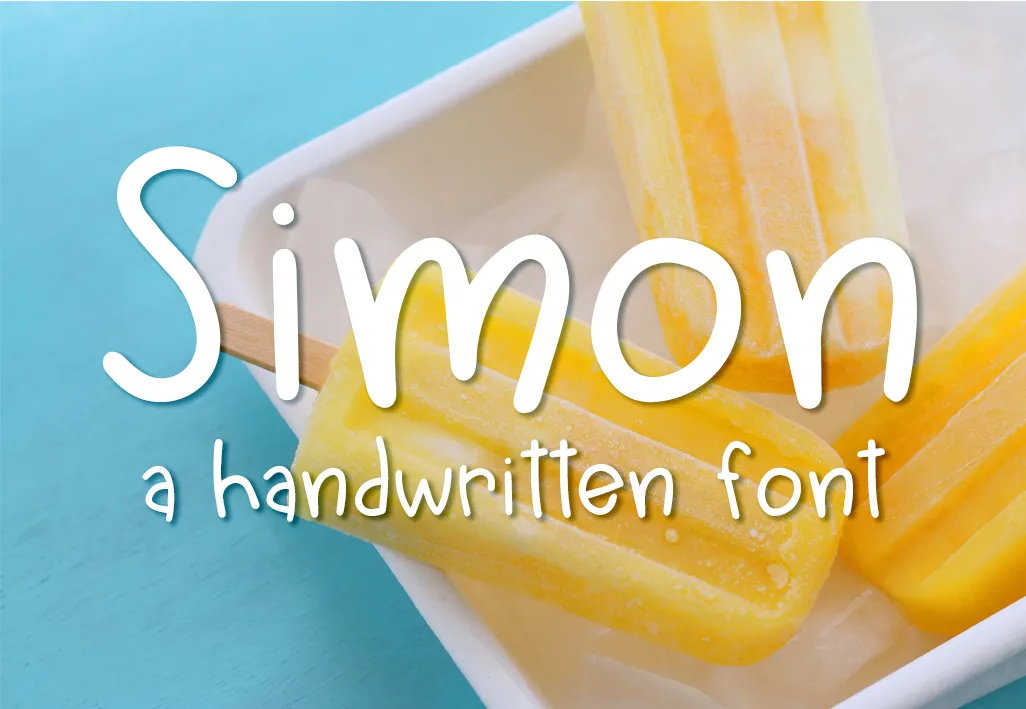
Simon Font
Aproveite para explorar a arte da escrita manual com nossa fonte ‘Simon Font’, projetada pelo incrível designer Groovyjournal. Esta fonte é perfeita para aqueles que buscam uma sensação natural e envolvente em seus trabalhos de design, seja para frases pessoais ou textos decorativos. A fonte ‘Simon Font’ possui um tom cuidadosamente pensado, oferecendo uma experiência visual única. Com traços leves e linhas sutis, ela traz à tona a essência da escrita humana em seu design. A disposição elegante e intuitiva dos caracteres permite que qualquer designer de gráficos use esta fonte para dar um toque pessoal aos seus trabalhos. Se você se delicia com nossas fontes e as utiliza constantemente, uma contribuição modesta em forma de doação pode fazer toda a diferença. Cada dólar contribuído vai diretamente para apoiar o projeto do designer Groovyjournal no desenvolvimento de novas fontes e na criação contínua de conteúdo visual. Com seu apoio, poderemos oferecer ainda mais recursos incríveis para todos nós que amamos o design gráfico. Obrigado pela sua atenção!